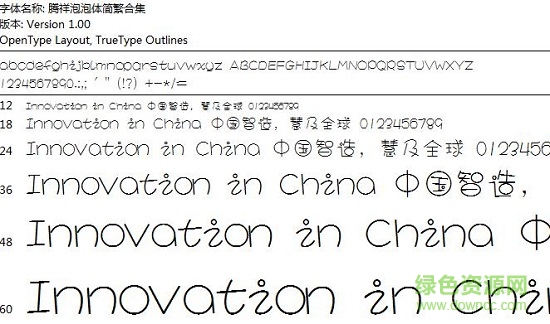
騰祥泡泡體是一款專為女生打造的可愛字體,這款字整體 效果會非常的q萌,用來作為主題文字再合適不過了,有需要歡迎下載使用!
騰祥泡泡體是騰祥字庫中一款非??蓯鄣?a href="http://m.lz0519.com/k/yishuziti/" target="_blank">藝術字體,這款字體整體呈現(xiàn)橢圓的泡泡形狀,并且點筆畫都換成的小圓圈,看上去特別的有意思!